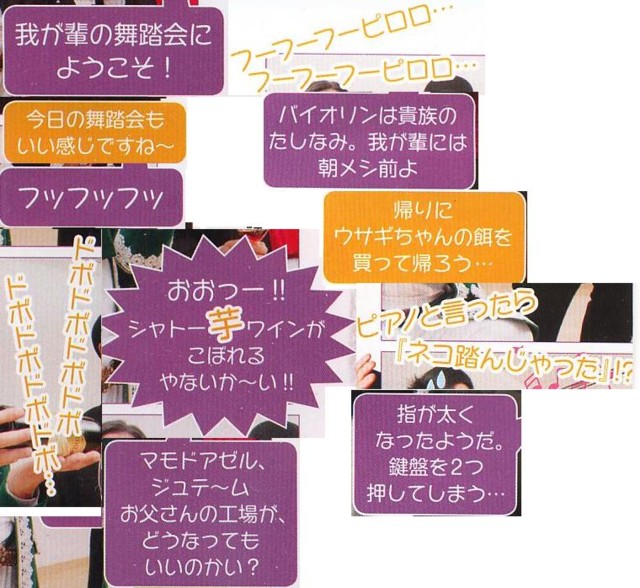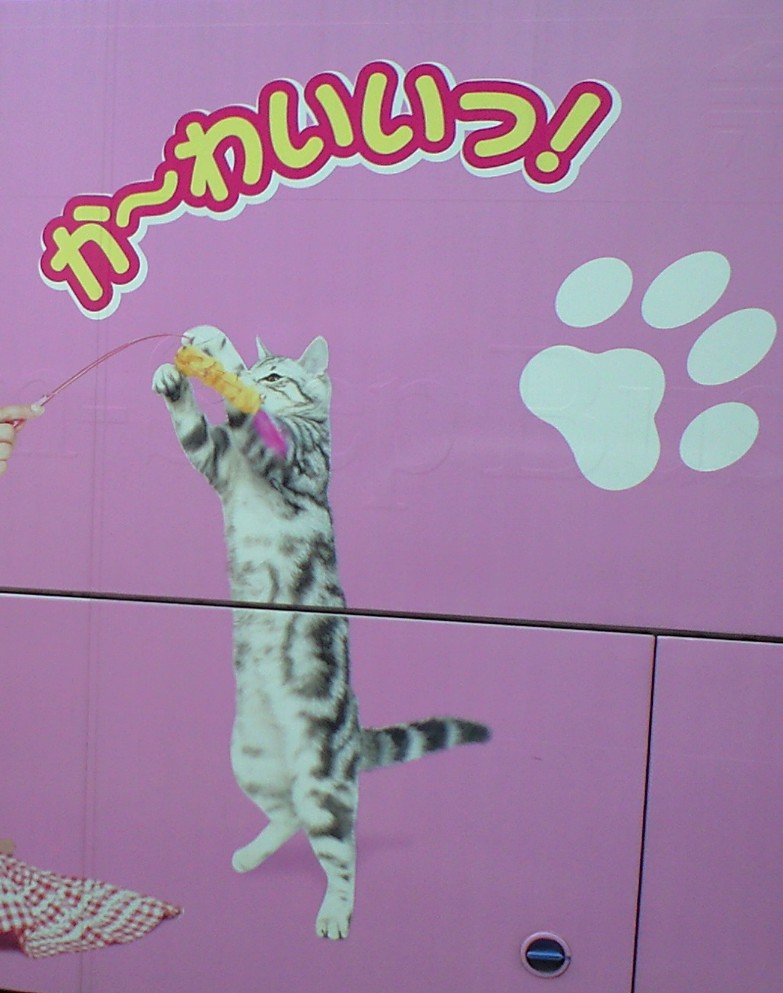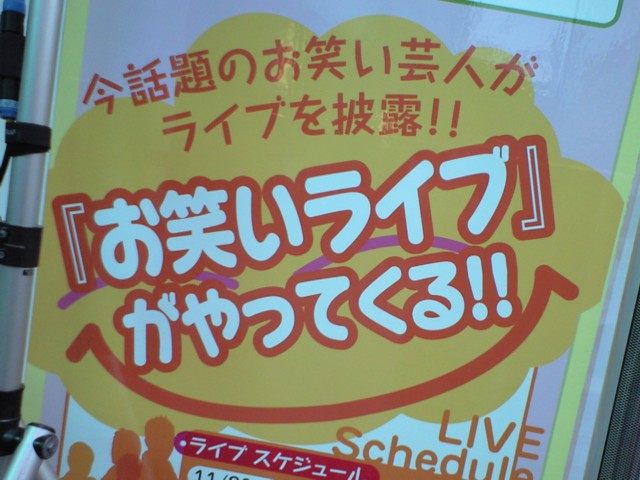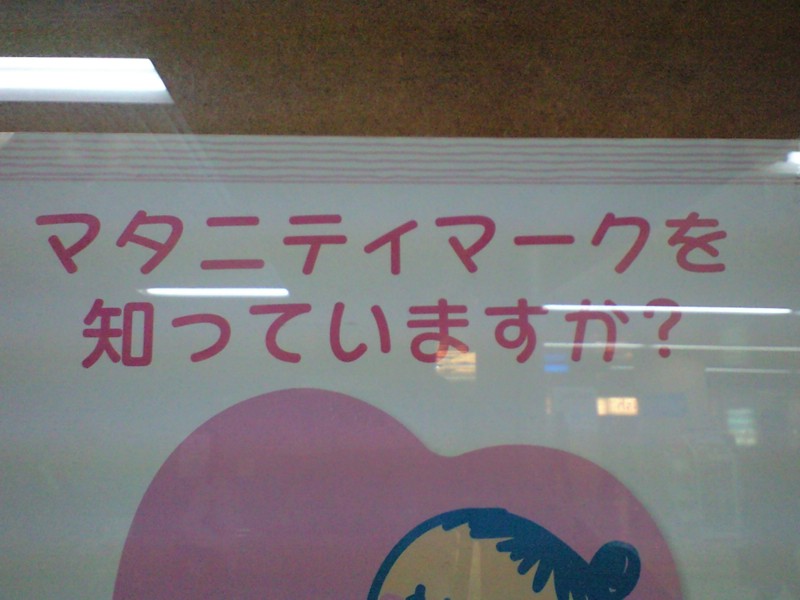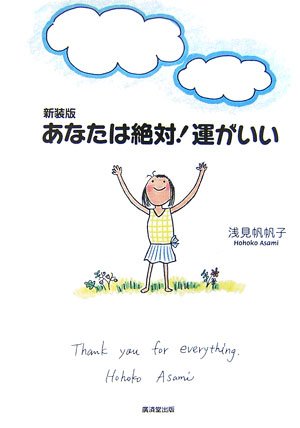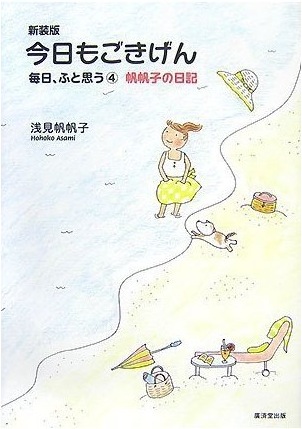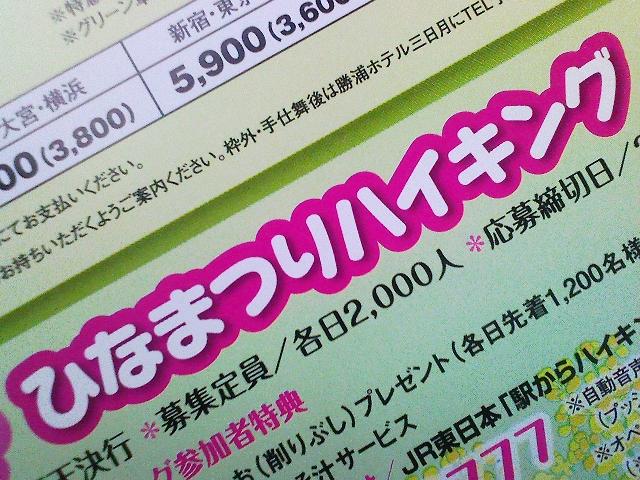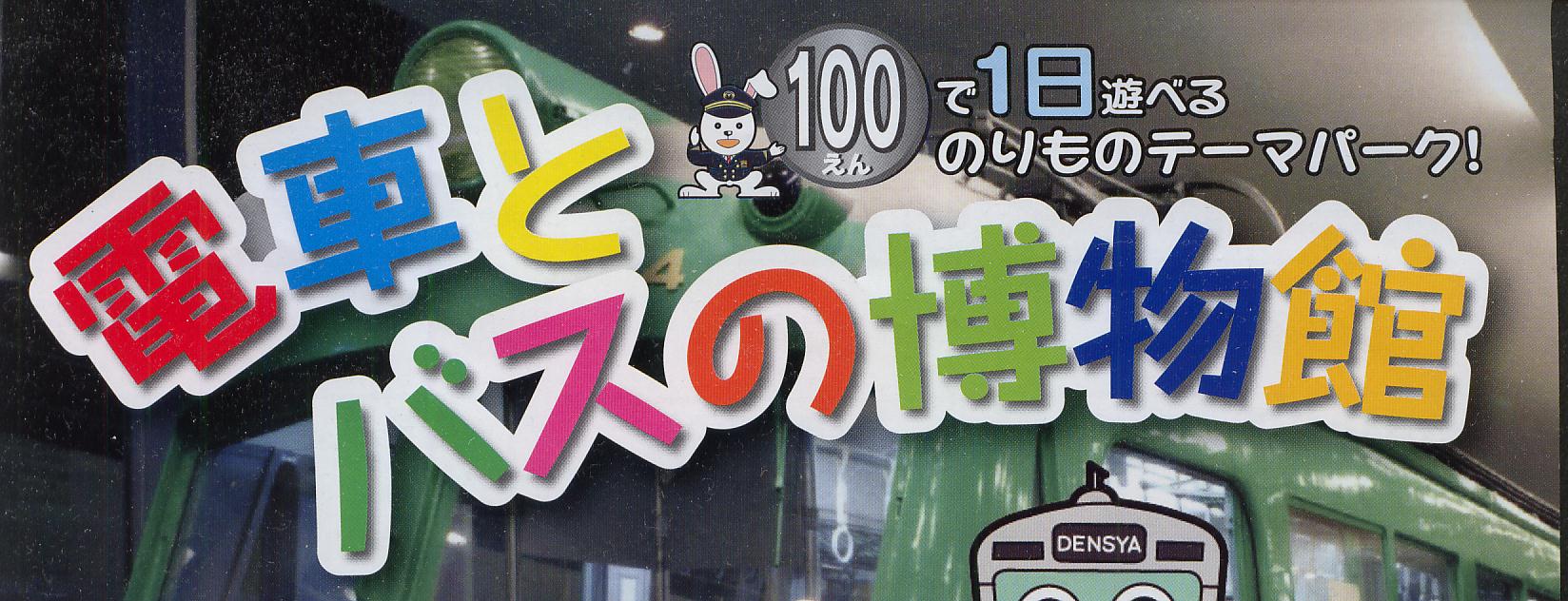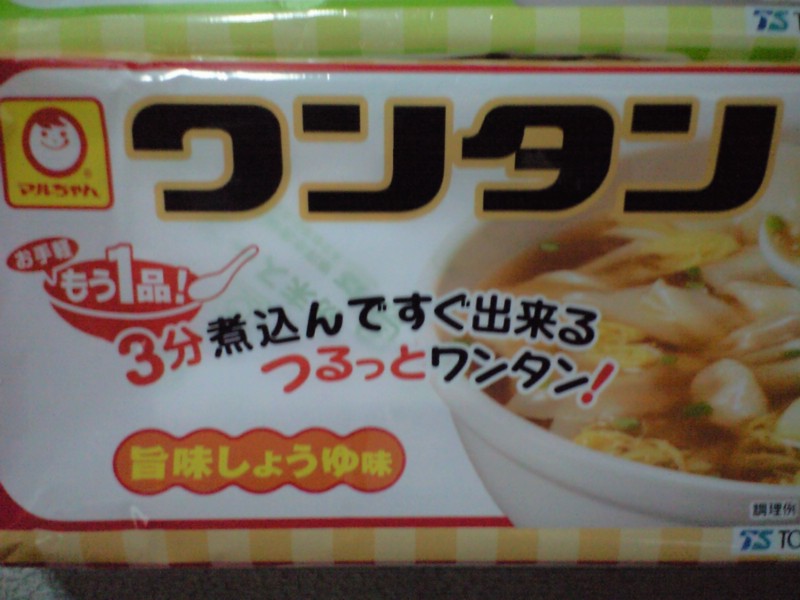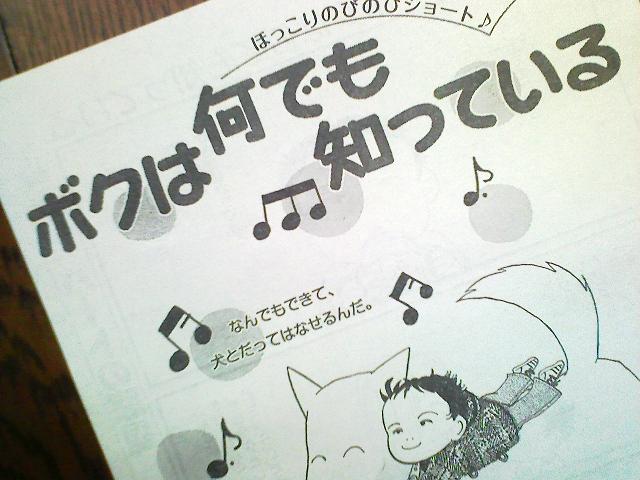
漫画の扉ページ さとうゆたか
女性向けの漫画雑誌だったかな。
海外旅行リーフレット さとうゆたか
カタカナ地名の部分です。
猫の本 さとうゆたか
書名:ニャンだふるワールド(裏モノJAPAN別冊)
発行:鉄人社
漫画の扉ページ さとうゆたか
KISSという漫画雑誌に連載されている「ありをりはべり」という作品。
漫画のフキダシ さとうゆたか
漫画アクションという雑誌に連載されている
「みんな自分ちのネコがいちばんカワイイと思ってるんでしょ?」という長い題名の漫画内で…。
女性向けマンガのタイトル さとうゆたか
太めのキャピーにアウトラインとシャドウが加えられています。
こちらにも。
化粧品の広告 さとうゆたか
女性向け漫画雑誌の表4にありました。
わんぱくも一緒です Mighty
「しねきゃぷしょん (chiphead氏作)」も入っていたりしますね。
雑誌の広告 さとうゆたか
ポポロの別冊で、小学生対象の雑誌のようだ。
区の広報紙 さとうゆたか
自分が住んでいる区が配布している物です。